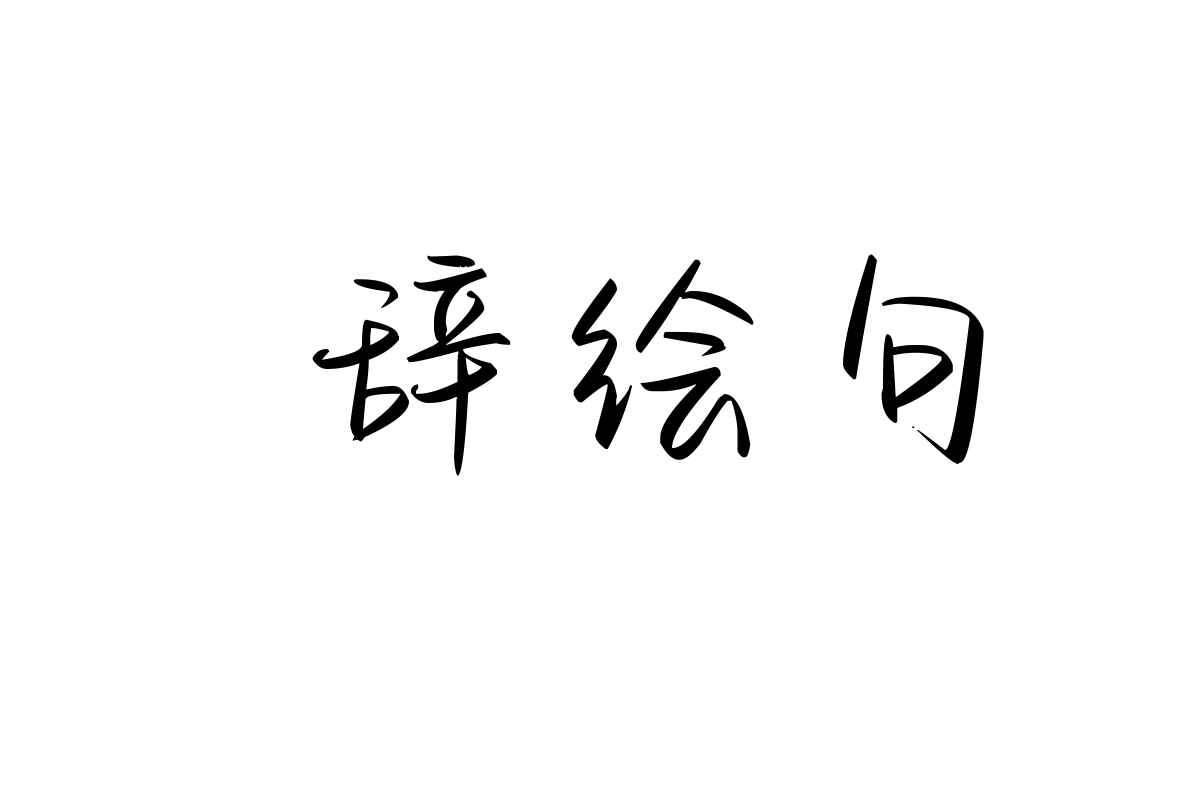
也字工厂综艺旁白体是一种专为综艺节目设计的字体,具有独特的风格和特点。这种字体的特点是:
1. 独特性:也字工厂综艺旁白体采用了综艺节目中常用的文字元素,如“也”字、“旁”字等,使得字体更加贴近综艺节目的氛围。
2. 易读性:由于是综艺旁白体,因此在设计时特别注重了易读性,使得观众能够轻松地阅读和理解节目内容。
3. 趣味性:在保持专业性的同时,也字工厂综艺旁白体还融入了一些趣味性的元素,使得字体更加生动有趣。
4. 可定制性:也字工厂综艺旁白体可以根据不同节目的需求进行定制,以满足不同节目的个性化需求。
总的来说,也字工厂综艺旁白体是一种专门为综艺节目设计的字体,具有独特的风格和特点,能够满足综艺节目的个性化需求。